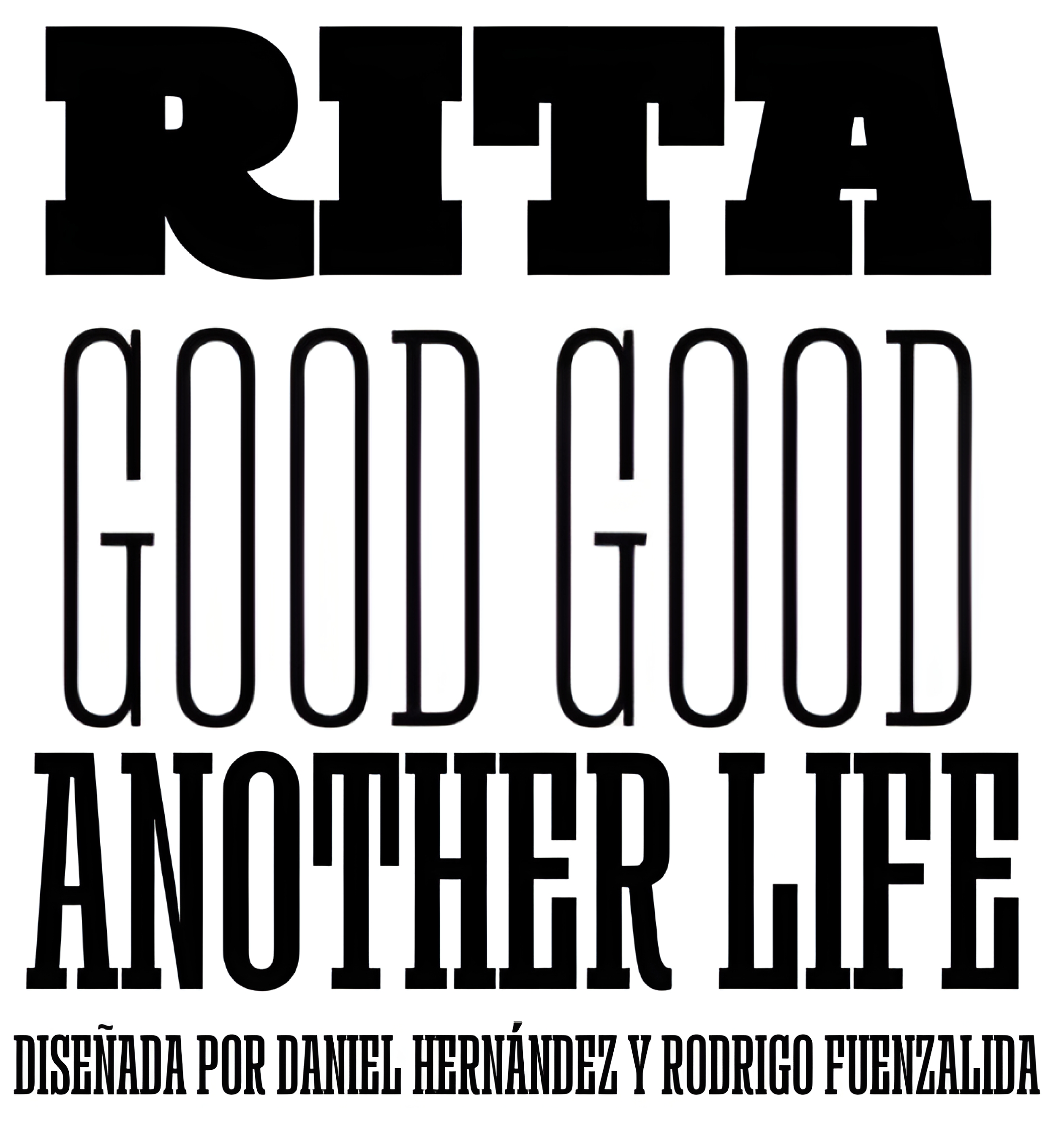
| Año | 2018 |
| Créditos | Daniel Hernández, Rodrigo Fuenzalida |
| Descripción | La publicación de este diseño más maduro es el resultado de un proyecto anterior de 1 solo estilo que se desarrolló en 2010. Rita, el nuevo diseño, ha pasado de ser un único estilo a ser una familia tipográfica completa, con una fuerte personalidad, ideal para textos cortos para diseños de gran impacto. Rita es un tipo de letra con gracias que ofrece una amplia gama de pesos y anchuras: desde una fuente fina y ultracondensada hasta una variante pesada para diseño de carteles. Su variedad de pesos y anchuras permite a los usuarios crear distintas composiciones, como títulos y texto de impacto o gráficos de gran impacto. Rita se presenta en 10 estilos e incluye un conjunto de 400 caracteres compatibles con más de 200 idiomas. Rita ha sido diseñada por Daniel Hernández con la colaboración de Rodrigo Fuenzalida. |
| Familia(s) | Rita |
| Estilos | 12 |
| Estudio | Latinotype |